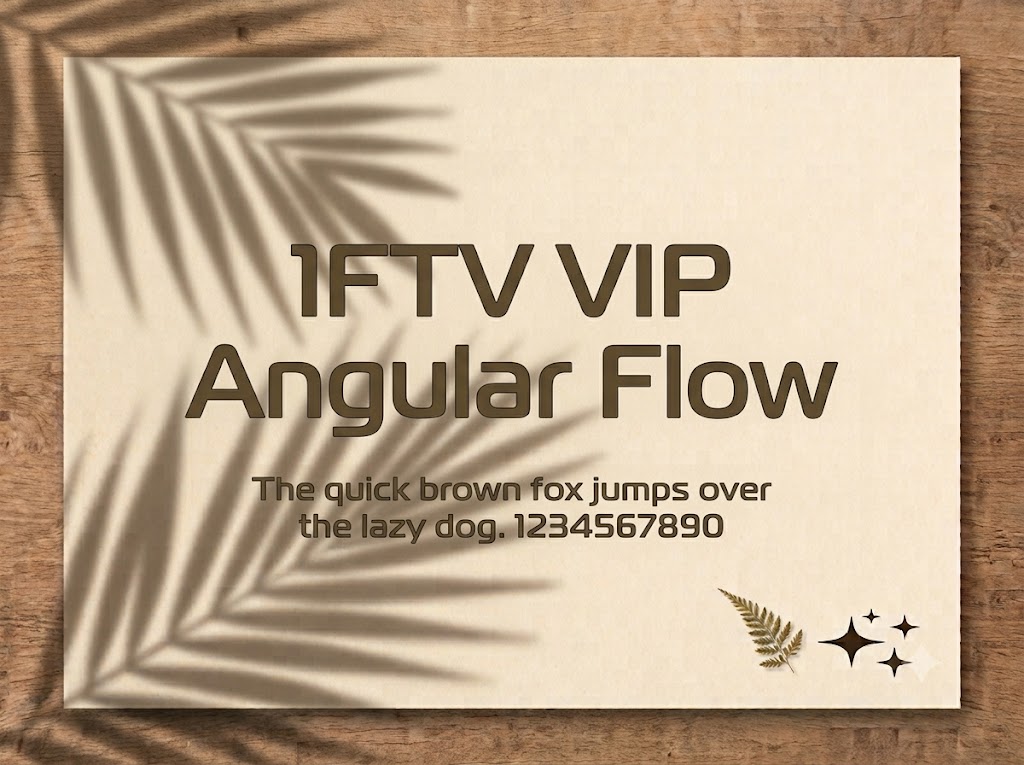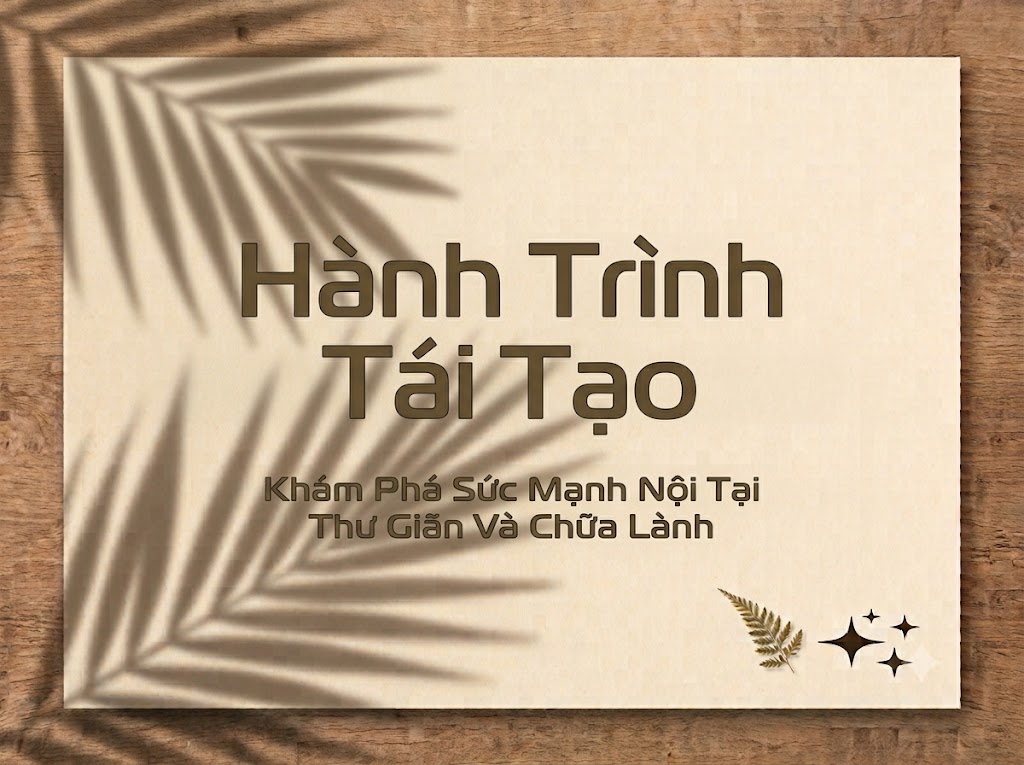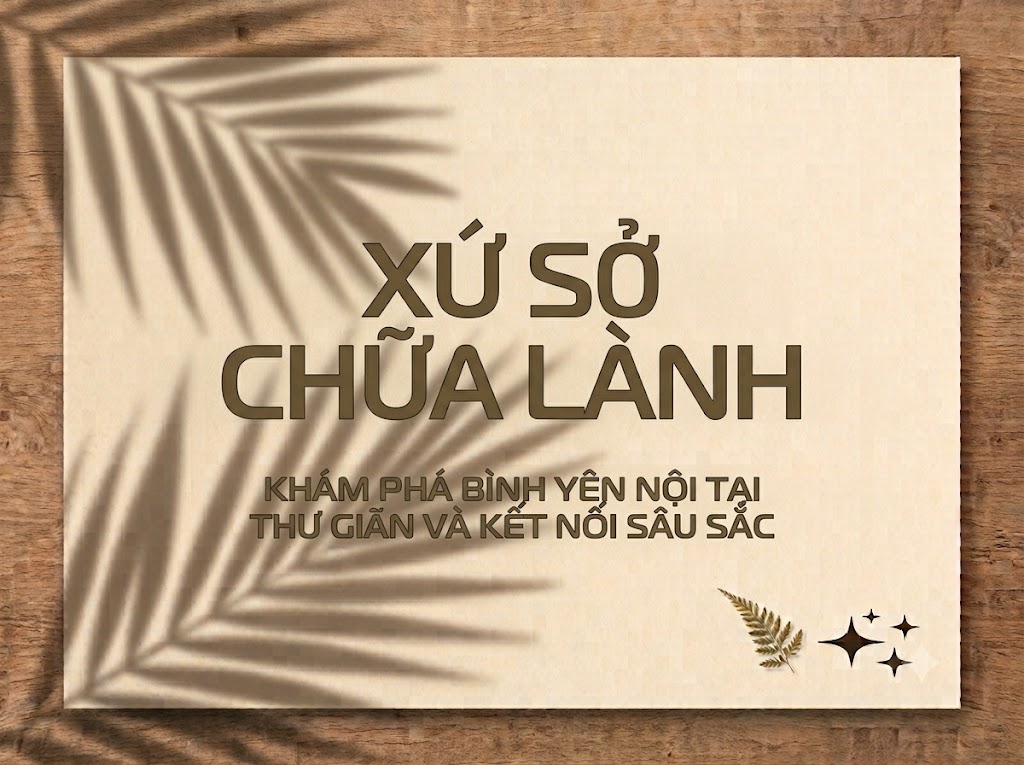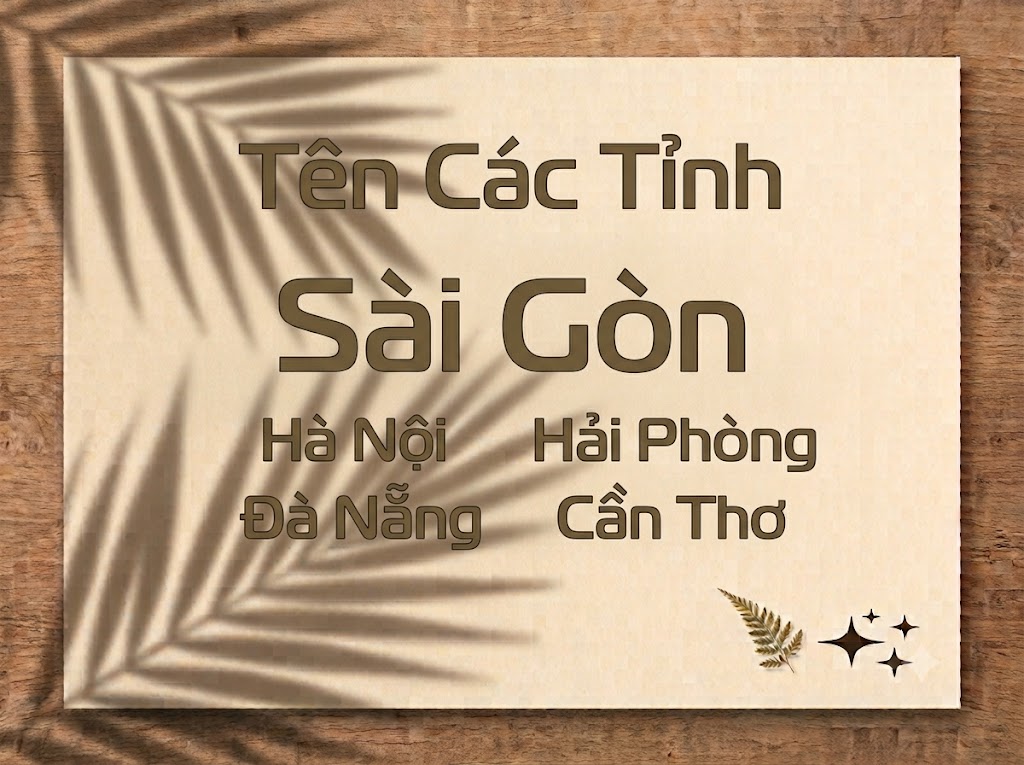
1FTV VIP Angular Flow
Khi định hình phong cách cho một ấn phẩm cao cấp, các nhà thiết kế thường tìm đến phông chữ Serif (có chân) để tôn vinh sự sang trọng và tính nghệ thuật. Tuy nhiên, nếu không được biến điệu khéo léo, các kiểu chữ Serif truyền thống rất dễ sa vào lối mòn già cỗi hoặc quá cứng nhắc.
Một giải pháp phá cách đòi hỏi sự giao thoa độc đáo giữa những đường cắt dứt khoát và nhịp điệu uyển chuyển tự nhiên. Đó chính là lý do font 1FTV VIP Angular Flow ra đời để tái định nghĩa sự thanh lịch hiện đại cho các tác phẩm đồ họa của bạn.
Giới thiệu về font 1FTV VIP Angular Flow
Font 1FTV VIP Angular Flow là một bộ chữ hiển thị có chân sở hữu phong cách nghệ thuật tân cổ điển (modern/transitional serif) đầy lôi cuốn và mang hơi hướng thời trang xa xỉ.
Nhờ cấu trúc kỹ thuật đồng bộ này, phông chữ có khả năng hiển thị vô cùng mượt mà, sắc nét, giúp bạn tự tin ứng dụng trên mọi phần mềm đồ họa chuyên nghiệp lớn mà không lo lỗi vỡ nét hay răng cưa khi phóng lớn bố cục.
Đặc điểm nổi bật của phong cách thiết kế Angular Flow
Đúng như tên gọi “Angular Flow”, kết cấu của bộ chữ là một vũ điệu đầy tính toán giữa tính hình học sắc sảo (Angular) và dòng chảy mềm mại (Flow):
Độ tương phản nét cao: Sự chênh lệch rõ rệt giữa nét thanh siêu mảnh và nét đậm dày dặn mang lại chiều sâu nghệ thuật cực kỳ tinh tế, gợi liên tưởng đến các tạp chí thời trang danh tiếng toàn cầu.
Biến điệu góc cạnh độc đáo: Các đầu chân chữ (serif) và nét dứt (terminals) không bo tròn hay loe rộng thông thường mà được vát nhọn phẳng góc phẳng phiu, tạo cảm giác vô cùng kiên định, hiện đại và thời thượng.
Hỗ trợ hoa – thường đồng bộ: Khác với các dòng font tiêu đề chỉ có chữ viết hoa, Angular Flow hỗ trợ trọn vẹn cả hai hệ thống chữ cái viết hoa và viết thường, giúp bạn tự do phối hợp linh hoạt để tạo ra một nhịp điệu đọc vô cùng thoáng mắt, tự nhiên.
Để phông chữ vận hành hoàn hảo trên mọi hệ điều hành từ Windows đến macOS, phiên bản font 1FTV VIP Angular Flow đã được tinh chỉnh kỹ lưỡng về mặt thông số nội tại:
Hệ thống khoảng cách chữ (kerning) và độ giãn dòng đã được tính toán khoa học, giúp các nét chữ mảnh mai khi đứng cạnh nhau luôn giữ được khoảng trống thẩm mỹ lý tưởng, không bị dính nét hay gây cảm giác rối mắt.
Tích hợp đầy đủ bộ chữ cái hoa – thường, dãy chữ số từ 0-9 cùng hệ thống ký tự đặc biệt, dấu câu thông dụng (
Bản Việt hóa chuẩn chỉnh từ đội ngũ 1FTV giúp các nhà sáng tạo nội dung hoàn toàn yên tâm gõ văn bản tiếng Việt có dấu mà không lo gặp phải tình trạng lỗi hiển thị ký tự hay nhảy font lỗi thời.
Hình ảnh demo thực tế của font 1FTV VIP Angular Flow
Kích thước nhỏ (12pt – 24pt): Nhờ khoảng trống bên trong ký tự (counter) được tính toán tỉ mỉ, các khối chữ viết thường và dấu tiếng Việt vẫn hiển thị rõ ràng, thanh thoát trên giao diện màn hình di động cỡ nhỏ.
Kích thước lớn (36pt – 72pt): Đây là đất diễn lý tưởng nhất để font chữ phô diễn toàn bộ sự kiêu sa, sắc sảo của các đường vát nhọn, tạo tác động thị giác mạnh mẽ chiếm trọn tâm trí người xem cho các dòng headline chính.
Ứng dụng của font Angular Flow trong thiết kế đồ họa và làm video
Sở hữu nét cá tính thanh lịch, sắc sảo và cấu trúc hoa – thường linh hoạt, font 1FTV VIP Angular Flow mở ra không gian ứng dụng vô cùng rộng lớn cho các dự án truyền thông hiện đại:
Làm tiêu đề video ngắn (TikTok, Reels, Shorts): Với dáng chữ đứng và kết cấu thanh lịch, phông chữ này hiển thị vô cùng ấn tượng trên các khung hình đứng tỷ lệ 9:16 dành cho thiết bị di động. Nó mang lại cảm giác lời thoại và dòng giật tít hiển thị một cách tự nhiên, cuốn hút mà không bị thô cứng như các kiểu chữ thông thường.
Thiết kế ảnh thu nhỏ YouTube (Thumbnail) phong cách lifestyle: Đặc biệt hiệu quả với các kênh làm nội dung về thời trang, lookbook, nghệ thuật, vlog chữa lành hoặc review không gian kiến trúc nhờ vẻ đẹp sang trọng, tinh tế.
Nhận diện thương hiệu và bao bì cao cấp: Phù hợp làm logo dạng chữ tối giản, biểu ngữ quảng cáo, menu nhà hàng/khách sạn sang trọng, thiệp mời sự kiện VIP hoặc thiết kế nhãn mác cho các thương hiệu nước hoa, mỹ phẩm phân khúc luxury.